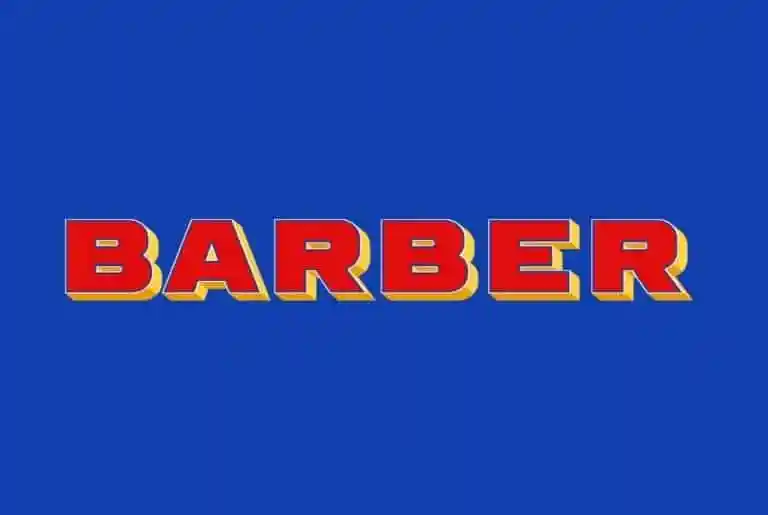
Barber Display Font
Introduzimos Barber Display Font — uma homenagem à arte vibrante do signpainting vietnamita. Este tipo de letra foi projetada baseado numa sobrevivente, um antigo sinal de barbear que se encontrava nas lojas comerciais da área de Cho Lon, na Saigon, durante o final dos anos 1980. As letras eram frequentemente pintadas à mão e dominavam os espaços urbanos até a sua desaparição no início deste século. Barber Display Font mantém esse espírito vibrante e artístico da antiguidade, agora revivendo essa rica tradição em um formato digital que pode ser aplicado na tipografia de grande tamanho. Perfect para estabelecimentos que valorizam o encanto do passado ou empresas que buscam uma fonte única para destacar seus sinalizações comerciais.